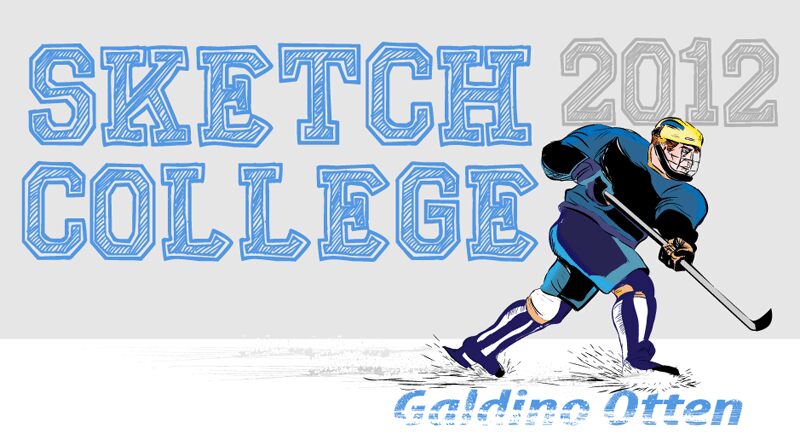
Sketch College, odważny font typu display stworzony przez Galdino Ottena, przywołuje nostalgiczny urok dawnej typografii szkolnej, wzbogacony o kreatywny twist. Jego wyrazista grubość i ręcznie rysowane detale tworzą estetykę, która jest jednocześnie przyciągająca wzrok i przystępna. Ten krój pisma emanuje nieformalną zabawą, dzięki czemu idealnie sprawdza się w projektach, które chcą się wyróżnić, zachowując przy tym szczyptę akademickiego sznytu.
Dzięki swojemu charakterystycznemu stylowi, Sketch College świetnie sprawdza się w różnorodnych projektach kreatywnych: od pełnych energii plakatów po angażujące grafiki w mediach społecznościowych. Jest szczególnie polecany do działań brandingowych poszukujących połączenia retro z oryginalnością, a także do materiałów edukacyjnych, które zyskują dzięki swobodnej, lecz mocnej oprawie wizualnej.
Dzięki Sketch College Twój zestaw narzędzi projektowych zyska nie tylko charakter, ale i wszechstronność – to wybór numer jeden, gdy Twój projekt wymaga fontu z osobowością i siłą przebicia.